ヒントの話06「フォント辞書の働き」
欧文フォントがカバーしているのは基本的にはラテンアルファベットという単一の体系ですが、日本語フォントは、漢字、仮名、英数字など、構造の異なる文字を含んでいます。このような複数の文字クラスを処理するための仕組みが「フォント辞書」です。
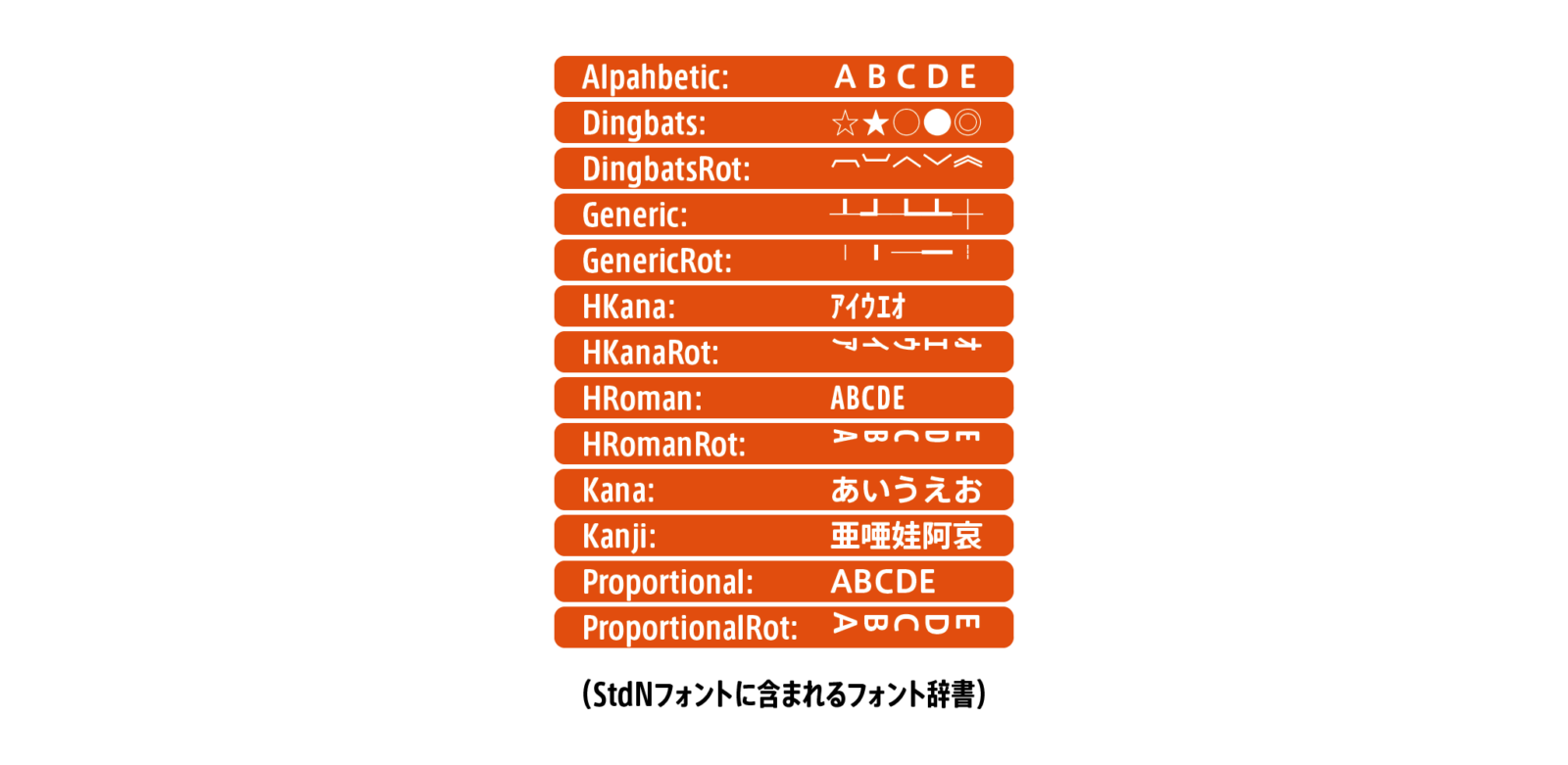
CFF形式の一般的な日本語OpenTypeフォントは、「漢字」「仮名」「プロポーショナル欧文」「全角欧文」「半角欧文」などの辞書を持っています。このシリーズで以前に紹介したBlueValuesなどについて、辞書ごとに異なる設定を持つことができます。
ラテンアルファベットは「ラインに揃える」システムに基づいてデザインされていますが、漢字や仮名は仮想ボディと呼ばれる正方形の枠を基準に配置されるため、特定のラインに合わせてオーバーシュートを抑制するという概念がそもそもなじみません。そのため、漢字や仮名用の辞書においては、BlueValuesには実質的には機能しないダミーの値が設定されます。